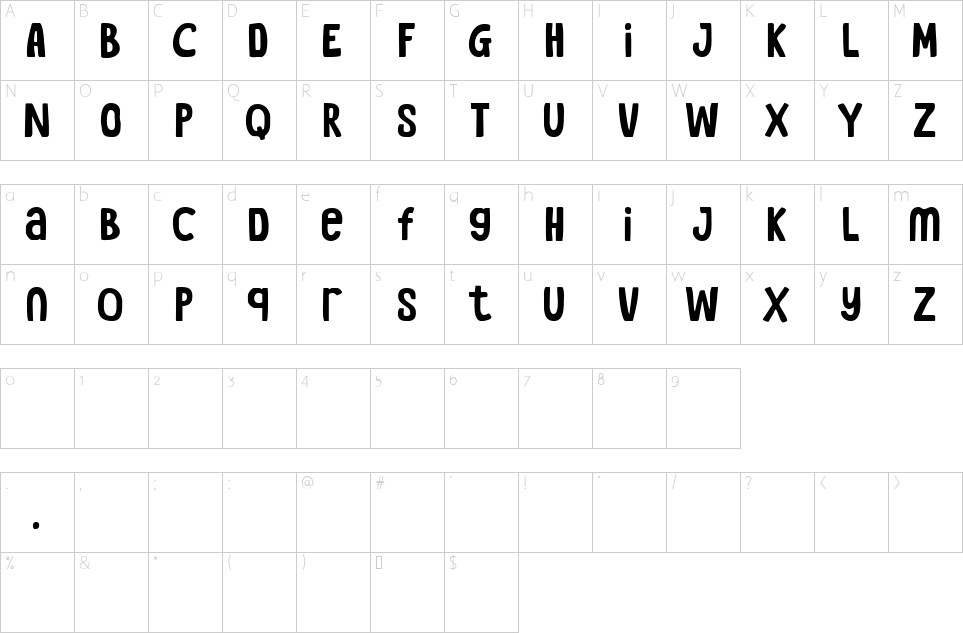
A Glubio Font é uma opção gratuita e divertida para designers que procuram manter seus projetos originais com personalidade. Desenvolvida pelo Flawless And Co, esta fonte oferece um visual único e desenho minimalista que pode adicionar um toque interessante a qualquer projeto de design gráfico. Embora seu criador não seja especificado, o design desta fonte se destaca pela sua simplicidade e facilidade de usar em ambientes Windows e Mac. Com uma alta popularidade entre designers, Glubio tem sido baixada pelo menos 162 vezes, sugerindo que os artistas encontram valor na maneira como esta font cria um equilíbrio perfeito entre modernidade e clássico. Não importa o tipo de projeto, a Glubio Font é uma escolha inteligente para quem busca fontes gratuitas com uma qualidade única.